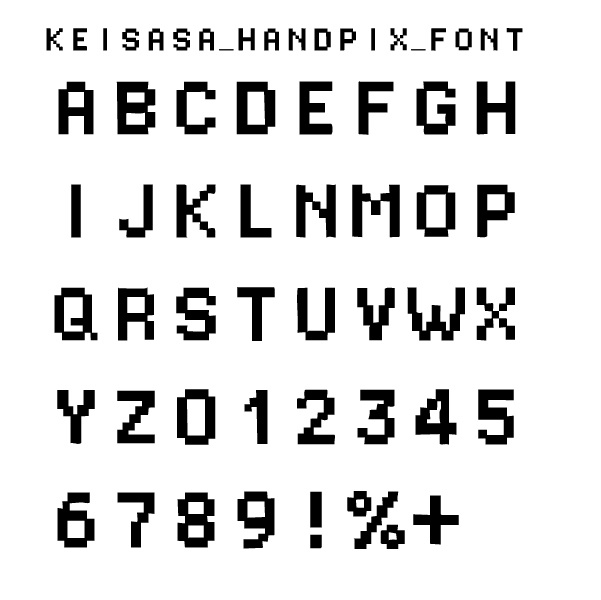
Keisasa Handpix Font︱手描きドットの、やさしいレトロ。
収録文字:A–Z(大文字)、0–9 フォーマット:TTF 商用利用:可 再配布・転売:不可 制作:sasasasaya / ksuke sasaki 手描き風のドットピクセルで構成された、温かみのあるレトロフォントです。 均一ではない線の揺らぎが、懐かしいゲームのような優しい印象を与えます。 タイトルロゴ、ドットアート、レトロゲーム風デザインに最適です。 A warm, retro-style pixel font designed with a hand-drawn touch. The subtle irregularities and organic lines give it a nostalgic, human feel — perfect for retro game titles, pixel art, and handmade-style designs.